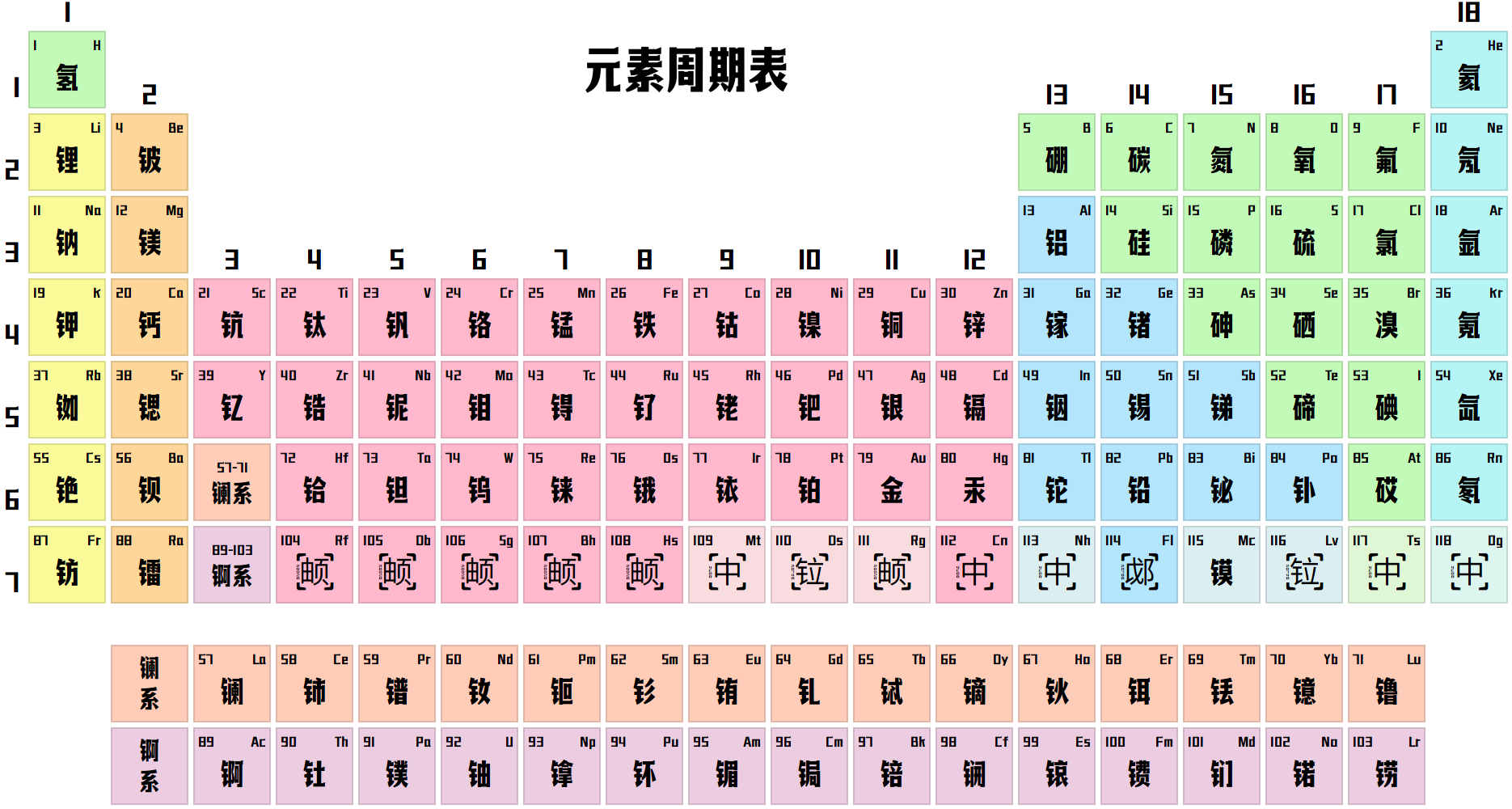
典迹悦动
典迹悦动(Monu YueDong)是设计师綿雲飴里基于卓特视觉开源字体中的卓特悦动黑优化而来的一款免费可商用标题黑体字体。
典迹悦动
由于原字体向右倾斜造成部分符号显示出现歧义,比如向上的箭头符号 ↑,在卓特悦动黑下容易被看成向右上方向的箭头 ↗︎,于是作者对其进行了修复,同时将原字体修正为了 0 度,且补充完善了现代汉语常用字、标点符号及部分拉丁字母等,形成了现在这款新的典迹悦动字体。
典迹悦动
典迹悦动保留了卓特悦动黑的复古印刷风格,笔画略粗,字重偏大,整体视觉感受厚重且富有力量感,很适合标题专用字体,比如海报设计、视频封面、网页大标题等,不建议长文正文。
典迹悦动